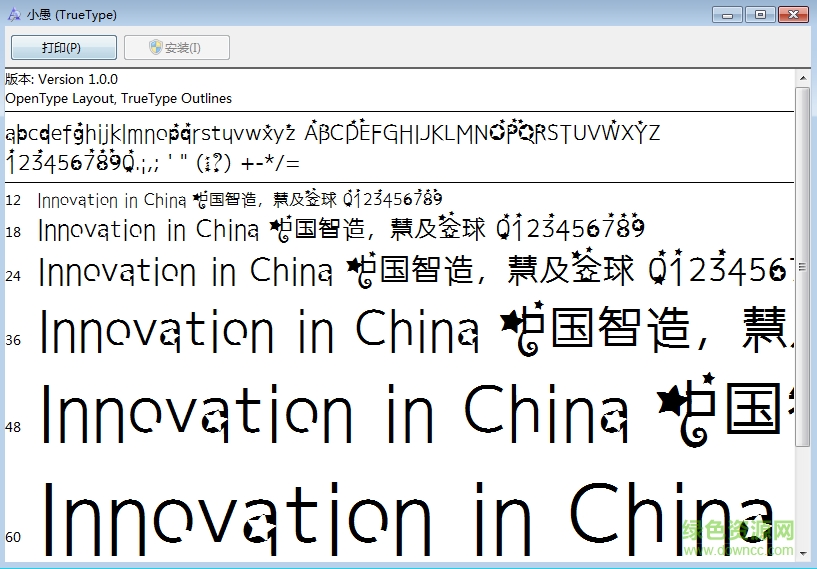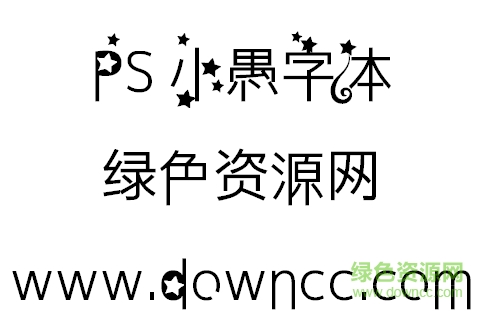
小愚字體是一款有著可愛星星點(diǎn)綴和創(chuàng)意奇特造型ps字體,充滿了少女和浪漫氣息,不規(guī)整的字體變化讓你的圖文更加生動(dòng),綠色資源網(wǎng)歡迎大家免費(fèi)下載!
小愚字體造型獨(dú)特,采用了趣味的星星符號(hào),每個(gè)漢字又有著與眾不同的造型,無(wú)論是漢字輸入還是英文字母都充滿活潑感,是一款很不錯(cuò)的藝術(shù)字體!
小愚字體線條纖細(xì)有力,帶有星星圖案,整體效果十分出眾,可以廣泛應(yīng)用于平面設(shè)計(jì)、廣告設(shè)計(jì)、報(bào)紙雜志、正文標(biāo)題等領(lǐng)域!